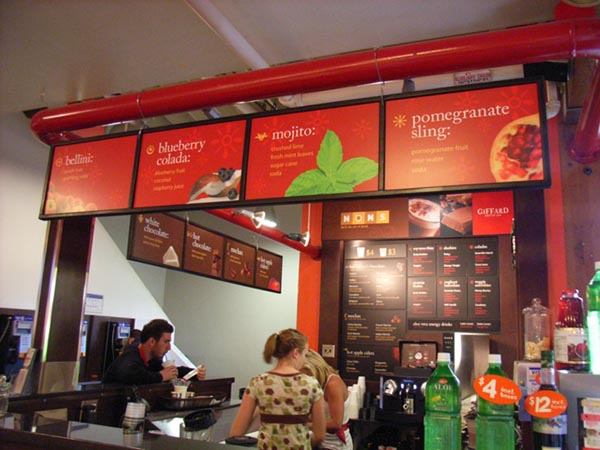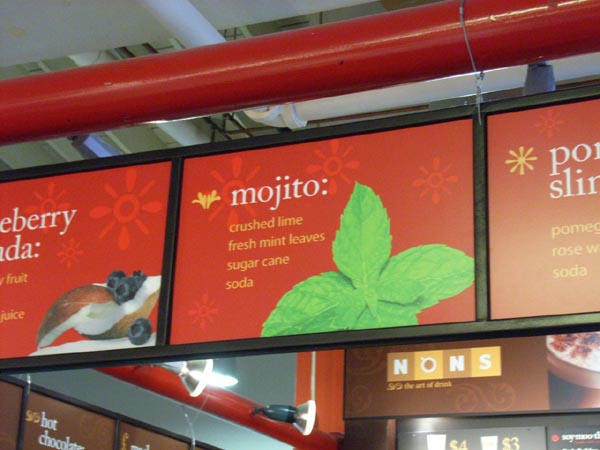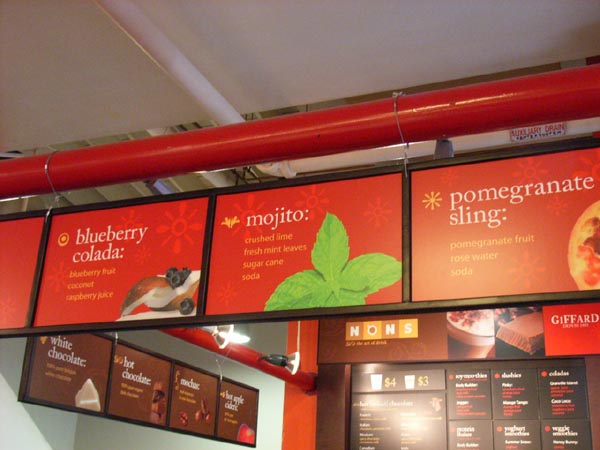
moji・・・?
何と今日は、カナダ特派員miko嬢からの報告です!
miko嬢は、7月下旬に行われたカナダでのカリコンファレンスに
参加していたのでありました。
なぜかmojitorという言葉に反応したとか・・・。それって、ねぇ・・・。
あれですよ・・・洗脳?(゚Д゚≡゚д゚)エッ!?
「mojito:」とな!
私も最初は、「mojitor」の飲物?
と驚きました〜。
惜しい〜でもいいですねぇ〜。
この、ちょっと外し感がたまりません!すっかりmojiさんは気に入ってしまいました!!
発音では「モヒート」と言うそうですが、ウィキペディアによればラムベースのカクテルの名前だそうです。mikoさん〜飲んだんですか?フフ。
お店の雰囲気もおしゃれですねぇ〜。こういう赤って好きですよね・・・あっちの人!
あっ、そうそう、私達はモジトルです。
モヒトルではありませんよ!(゚∀゚)アヒャヒャ
ここは ikuko さんに連れて行ってもらった、バンクーバーのグランビルアイランドにある市場の中なんですが、そんな強い?お酒を飲みながら、夕飯の買い物をするんでしょうかね?現地の方は。